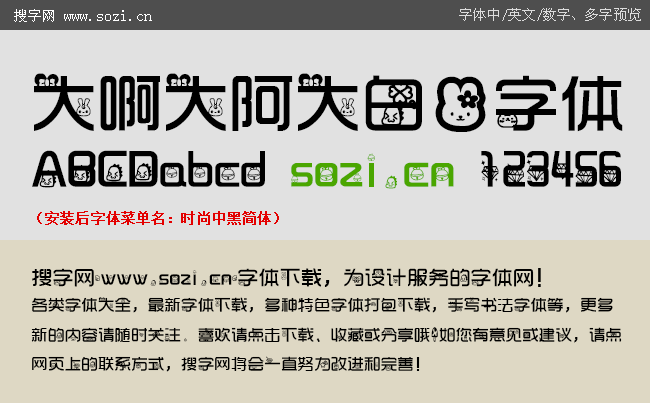
大啊大阿大白兔字體
搜字網(wǎng)給大家提供一款很有趣的手機中文字體下載。修改者給他起了個大啊大阿大白兔字體這么萌的名字,這款手機字體是在時尚中黑字體上進(jìn)行修改,筆畫間插入了有趣的卡通動物圖案。真是趣味性實足的一款手機字體,該中文字體個性實足,趣味性強,又保持了文字的識別度,特別適合喜歡手機字體個性一些的朋友在手機上安裝使用。